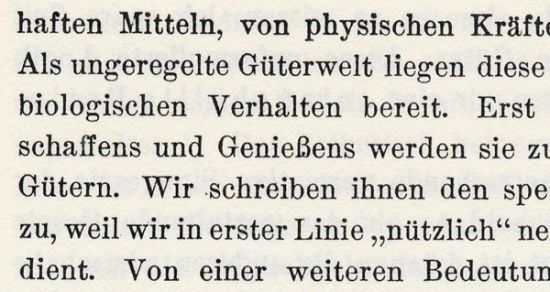
Buchschrift von 1921
Sallü, in einem Buch von 1921 aus dem Niemeyer-Verlag wird folgende Schrift verwendet:
Mein Tipp auf die Schnelle und ohne Unterlagen:
Gruppe IV - Klassizistische Antiqua - Amts-Antiqua mager
D.Stempel AG, Frankfurt am Main
Erstguß 1909
Heinrich Hoffmeister
Als Neu-Auflage unter dem Namen
Madison im Jahre 1965 erschienen.